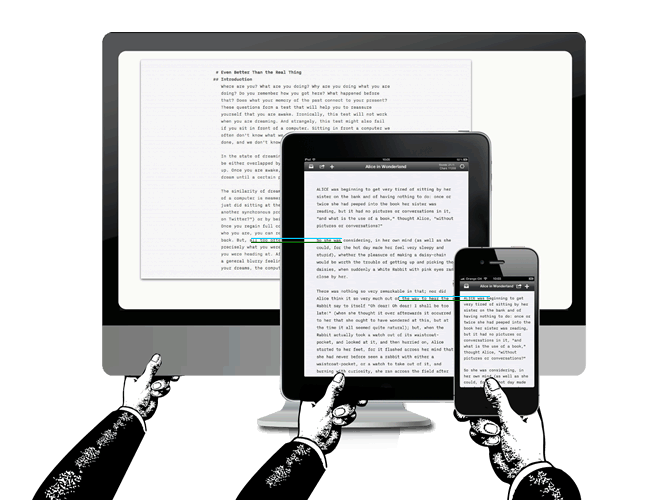
Responsive Typography
Nachdem das Web inzwischen nicht mehr nur auf stationären Computern stattfindet, sondern auf einer Unzahl unterschiedlicher Endgeräte mit darüber hinaus unterschiedlichen Bildschirmqualitäten, entstehen auch für die Typografie neue Herausforderungen, die über den Einsatz von Webfonts hinaus gehen. Deswegen hat sich Oliver Reichenstein, Inhaber der Information Architects und begnadeter Redner dem Thema »Responsive Typography« gewidmet, das er direkt in der »iA Writer App« umgesetzt hat: Schriftschnitt, Spationierung, Schriftgröße, Zeilenabstand, alles wurde auf die jeweiligen Ausgabegeräte angepasst. Was man unter »Responsive Typography« versteht erklärt uns Oliver Reichenstein im Interview.
Den Grundansatz des Lesens in verschiedenen Medien …
… kann ich gerne unterstützen.
Die Sache mit den Grauwert-abgestuften Webfonts schießt dann doch über das Ziel hinaus. Nicht, dass man sich um diese Problematik (der unterschiedliche Fetten in unterschiedlichen Rasterizern) keine Gedanken machen solle. Aber die normalen typografischen Parameter der Schriftwahl und des Schriftsatzes haben in der Summe einen so viel größeren Einfluss auf eine gute Webtypografie, als dieses Detail.
Außerdem sehe ich kurzfristig auch technisch keine Möglichkeit, jeden Browser-Client auf allen möglichen Mobil- und Desktop-Geräten entsprechend dynamisch mit Grauwert-abgestuften Fonts zu bedienen. Der Aufwand jede Rasterizer-Variante und Bildschirmauflösung speziell zu bedienen steht doch in keinem Verhältnis zum Nutzen.
Vor allem, weil die Lesegewohnheit des Lesers ohnehin auf sein System hin geprägt ist ...
Einem Gestalter mag die Schriftdarstellung des jeweils ungewohnten Systems "falsch" vorkommen und er will was dagegen unternehmen. Der Leser hingegen liest ständig auf seinem System und es fällt ihm gar nichts auf.